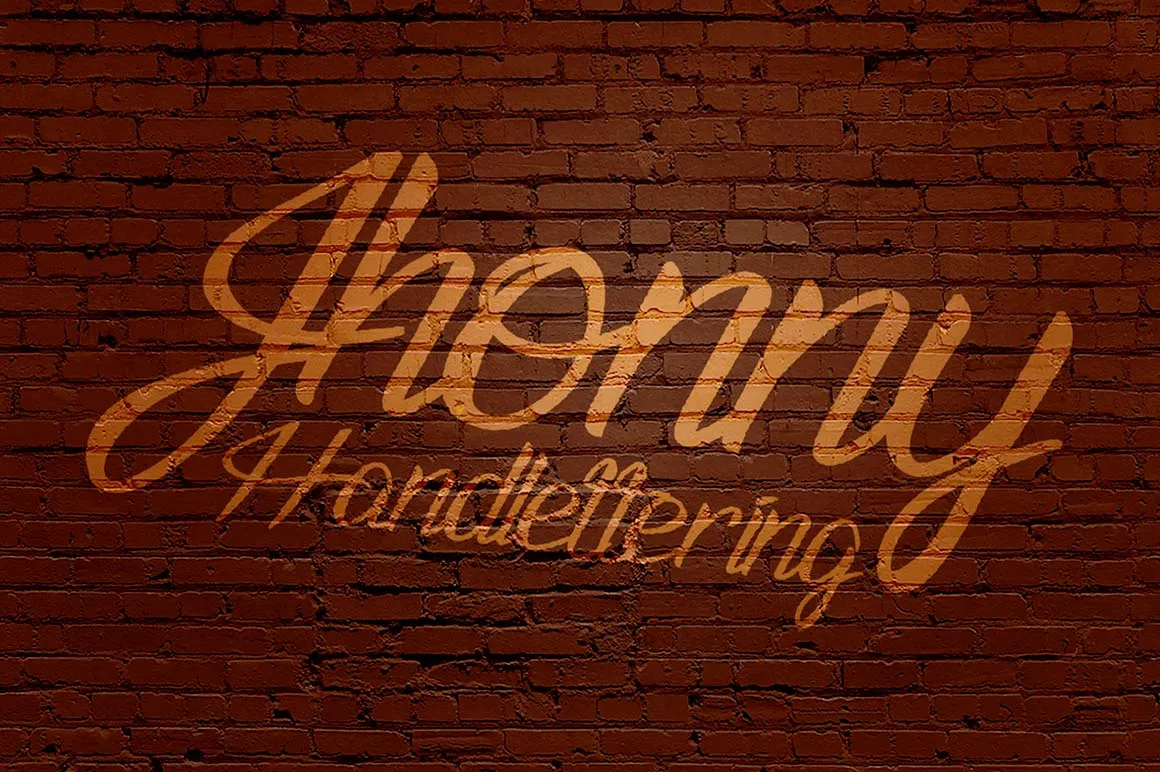
Jhonny Handlettering Font – Fonte Grátis
Jhonny Handlettering Font
Esta maravilhosa fonte script foi criada pela Inksun Mildertype e traz uma escrita manuscrita única e envolvente. Hamilton é o designer por trás desta incrível ferramenta gráfica, perfeita para aqueles que desejam adicionar um toque de personalidade a suas criações digitais. O Jhonny Handlettering Font é perfeito tanto para designers profissionais quanto para iniciantes, oferecendo uma escrita manuscrita fluida e expressiva. Esta fonte permite que você personalize o tom e os detalhes do texto conforme necessário, criando um texto com uma aparência autêntica e única. Com seu design cuidadosamente trabalhado por Hamilton, a Jhonny Handlettering Font é ideal para designers gráficos buscando incorporar um toque de hand lettering em seus projetos. Seja para criar selos personalizados ou adicionar um texto exclusivo ao topo da sua página, esta fonte oferece flexibilidade e qualidade impressionantes. Aqui está uma opção perfeita para quem busca um novo recurso gráfico que não apenas enriqueça a aparência de suas criações, mas também adiciona um toque pessoal e único. Descarregue-a agora e experimente o poder desta fonte incrivelmente fluida e envolvente.